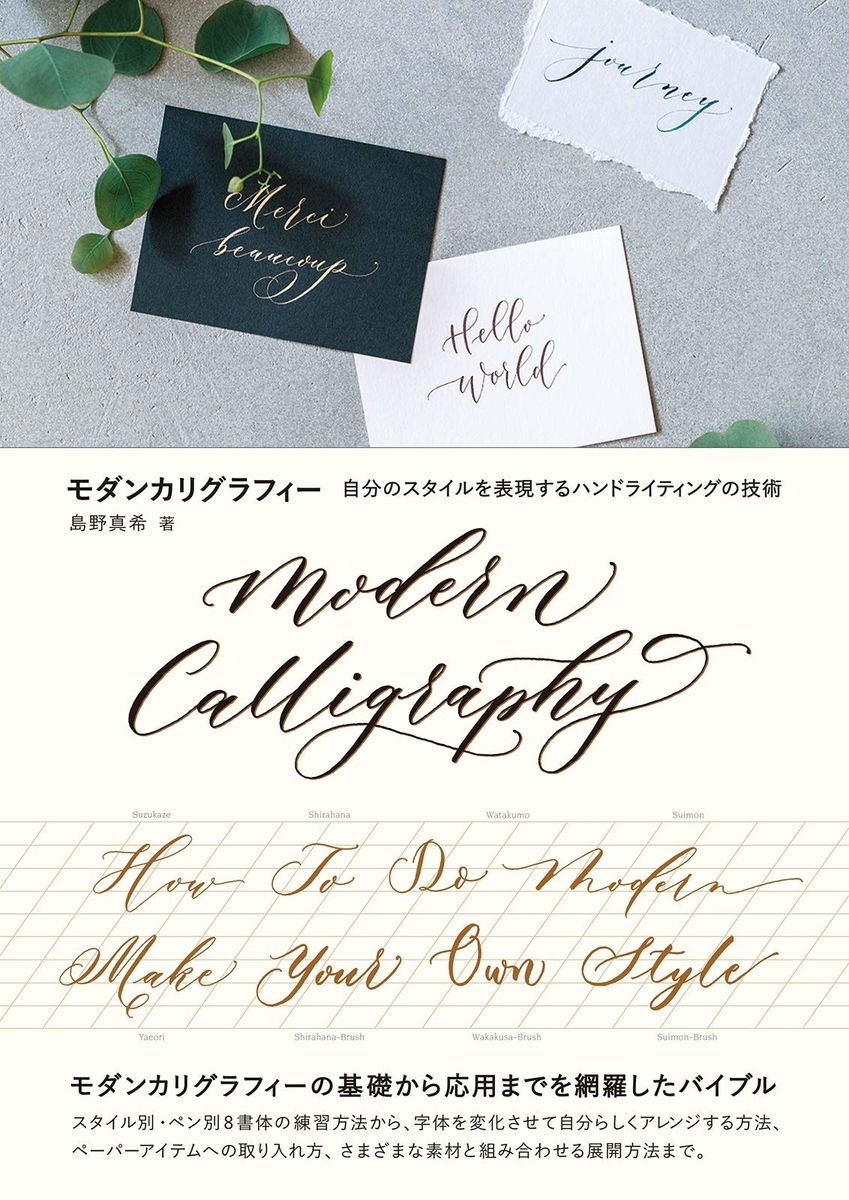
モダンカリグラフィー 自分のスタイルを表現するハンドライティングの技術/モダンカリグラフィー スタートセット
書道家、カリグラファーとして活躍する島野真希氏による日本初のモダンカリグラフィー指南書「モダンカリグラフィー 自分のスタイルを表現するハンドライティングの技術」がビー・エヌ・エヌ新社から2019年6月14日に発売された。
「モダンカリグラフィー 自分のスタイルを表現するハンドライティングの技術」は、実践的な練習方法でスタイル別・ペン別の8書体と例文をしっかり書けるようになる基礎編、自分らしい字体に変化させレイアウトや配色のデザインを考えるアレンジ編、イラストレーションと組み合わせたり紙以外の素材に書いたりアイテムに落とし込んでスタイリングする展開編、の3部構成になっている。
モダンカリグラフィーの基礎から応用の入り口までを網羅したバイブルとして、カリグラフィー初心者の方、書き文字をワンランクアップさせて別の趣味やお仕事と組み合わせたい方、自分だけの文字を追求してオリジナルの世界観を作りたい人までを対象に、幅広いリクエストに応えている。
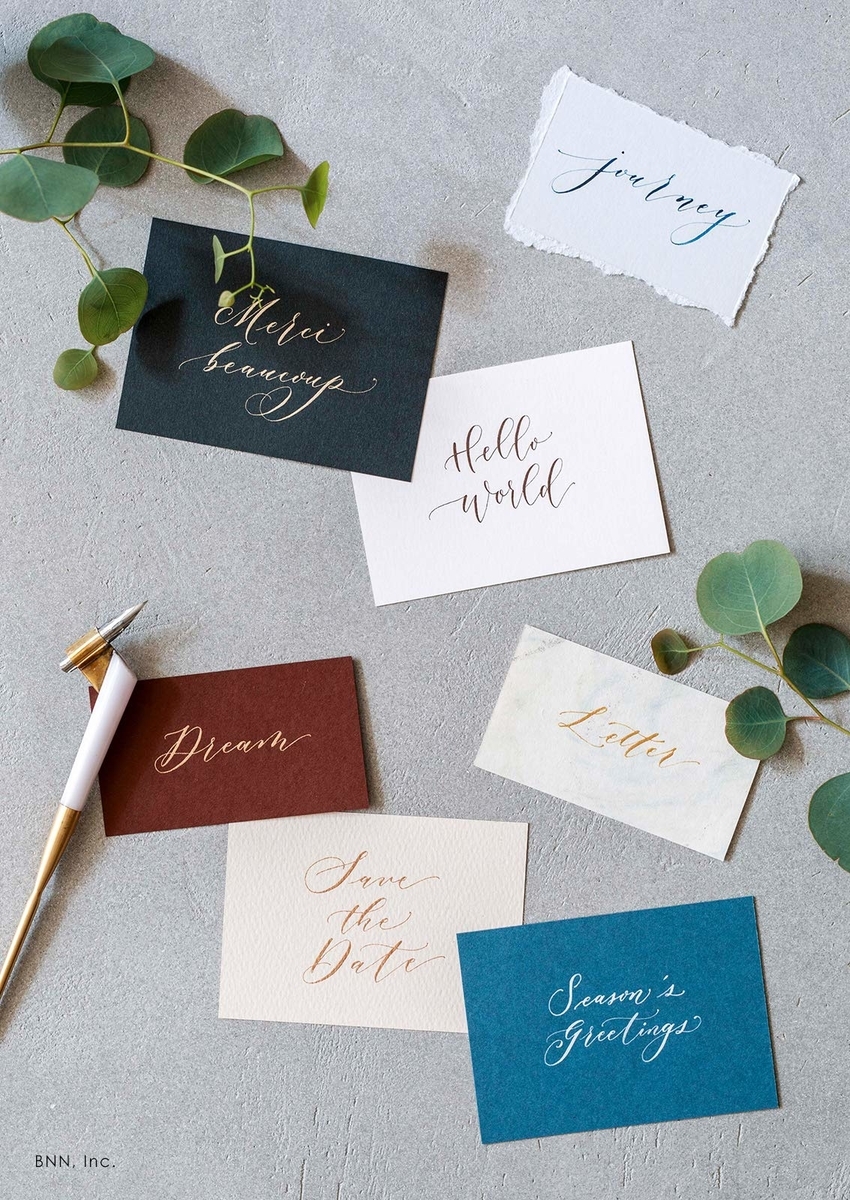
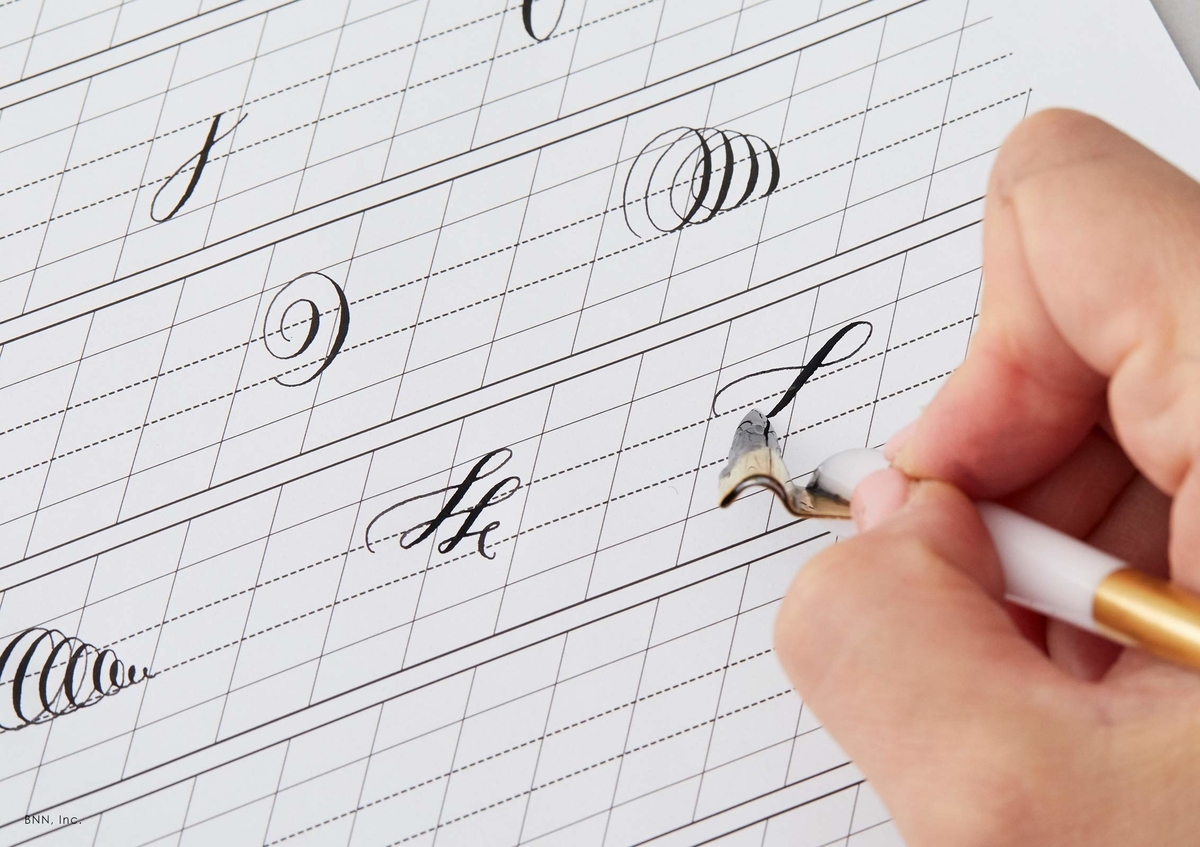
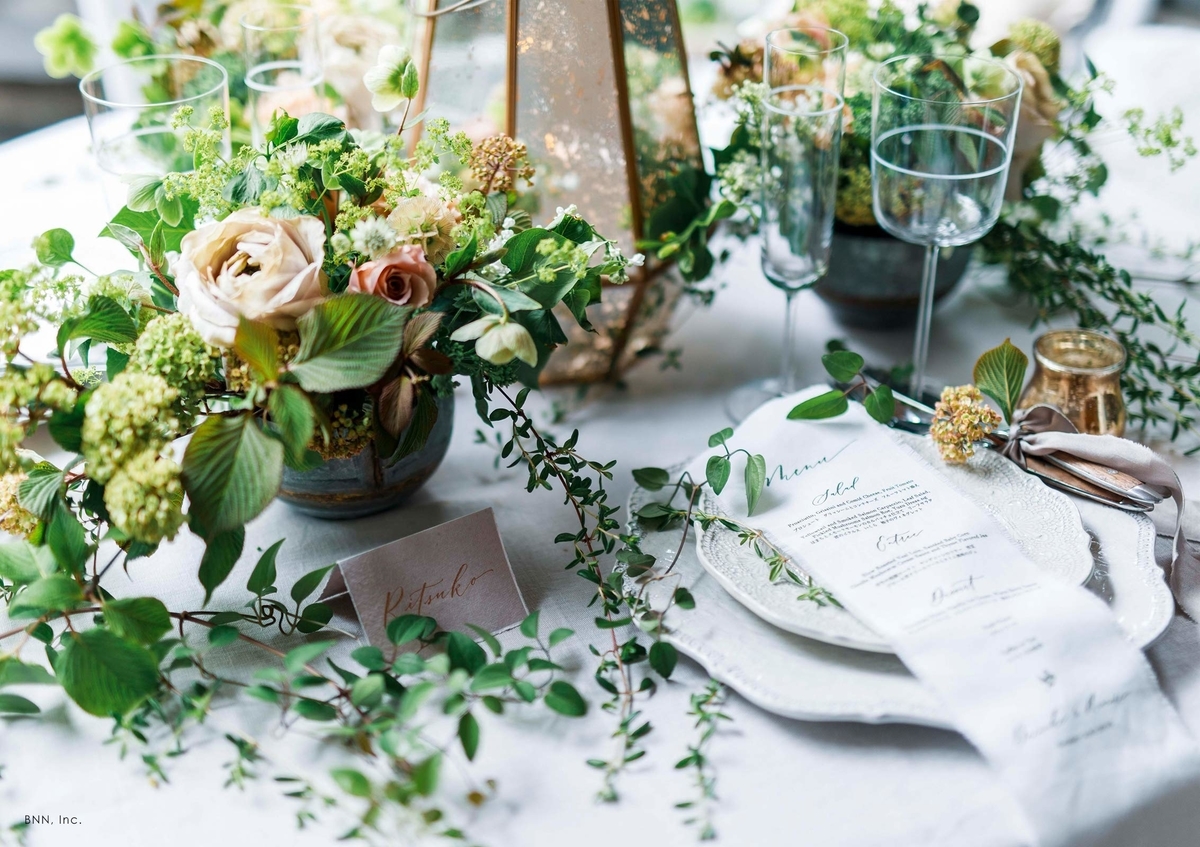
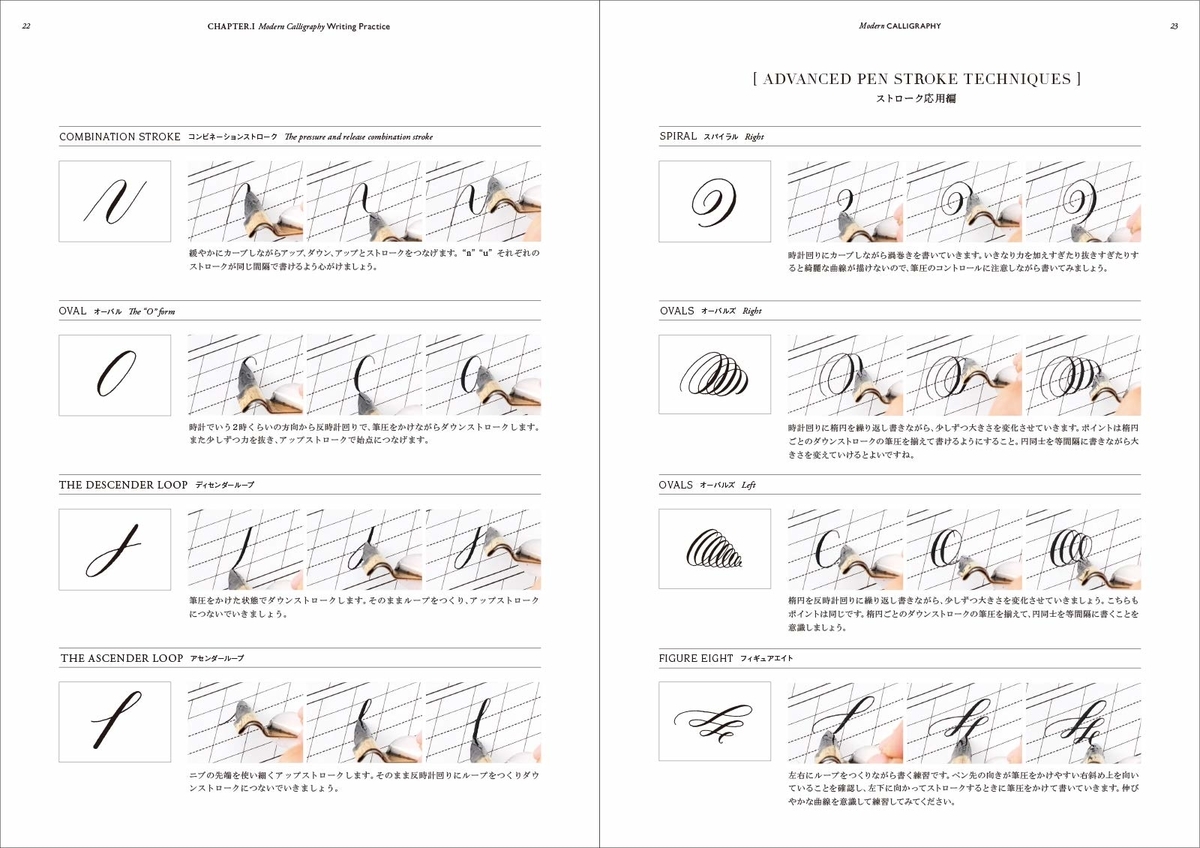
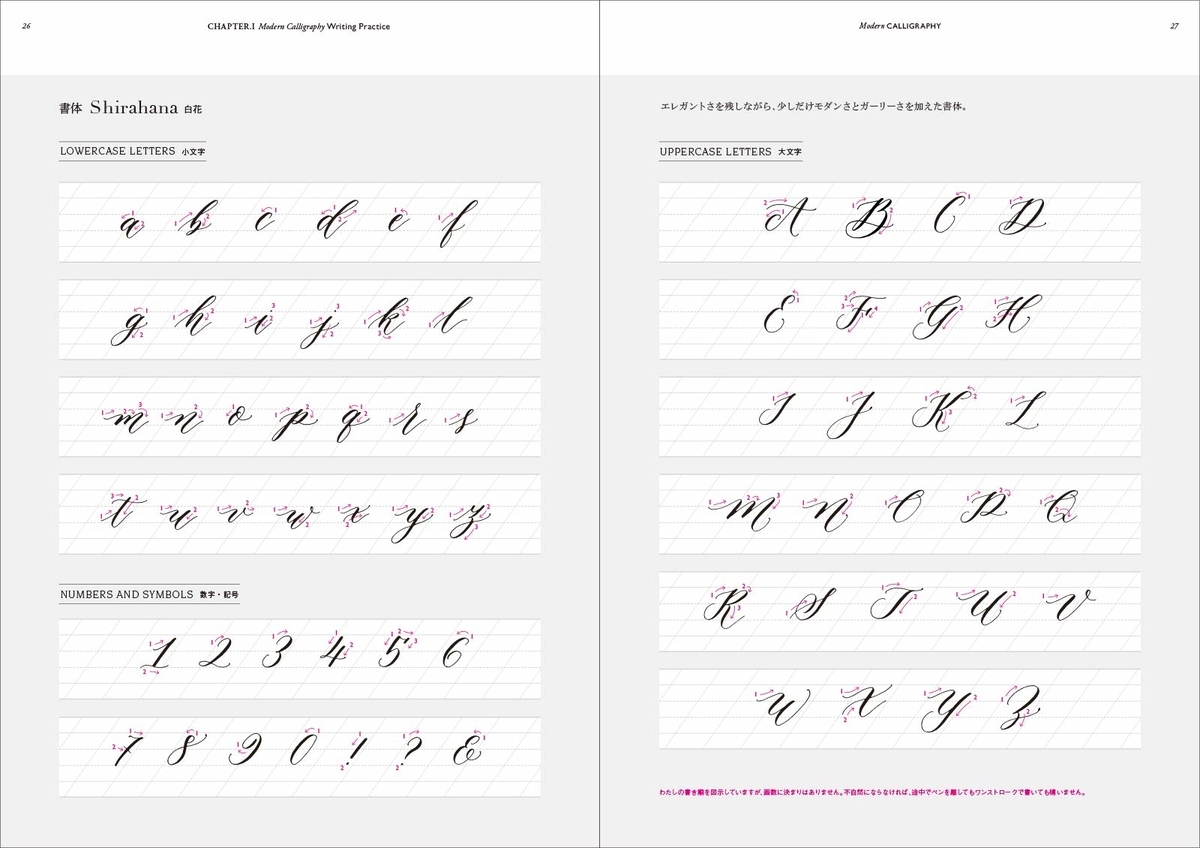
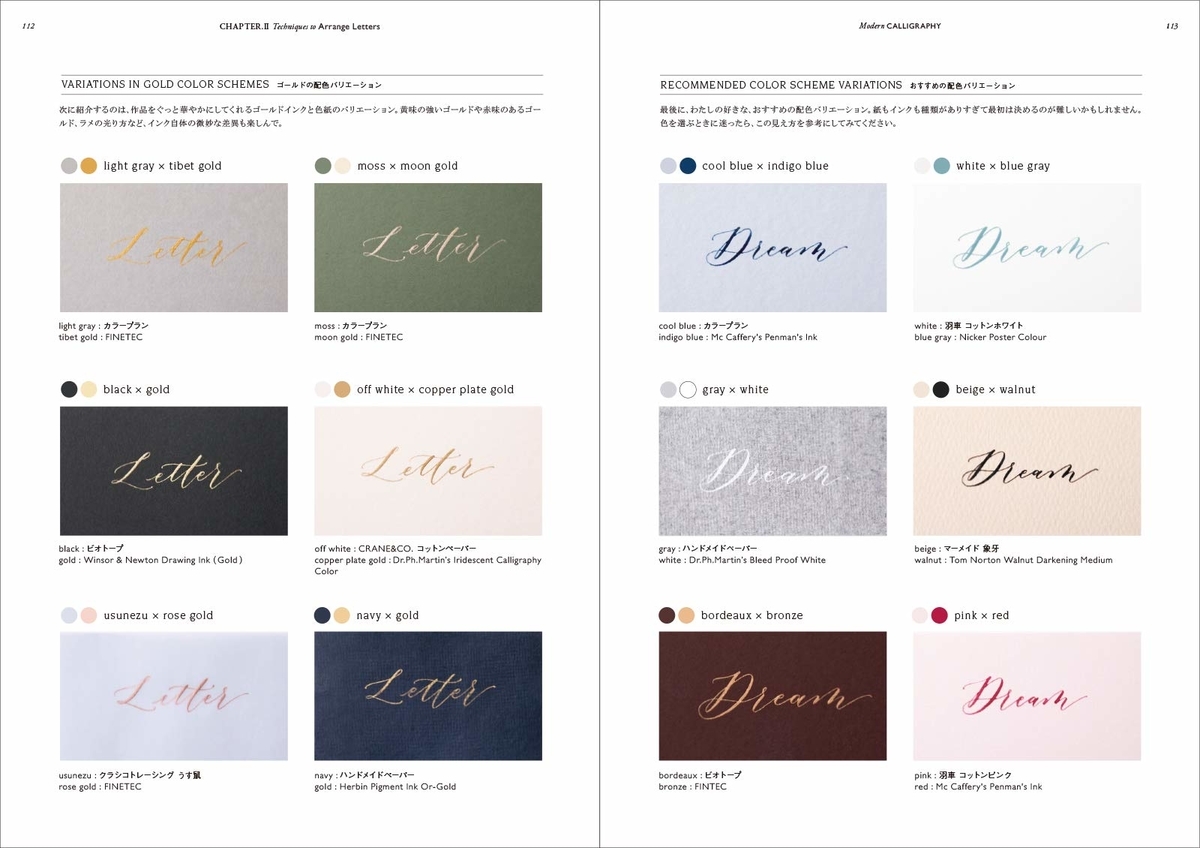
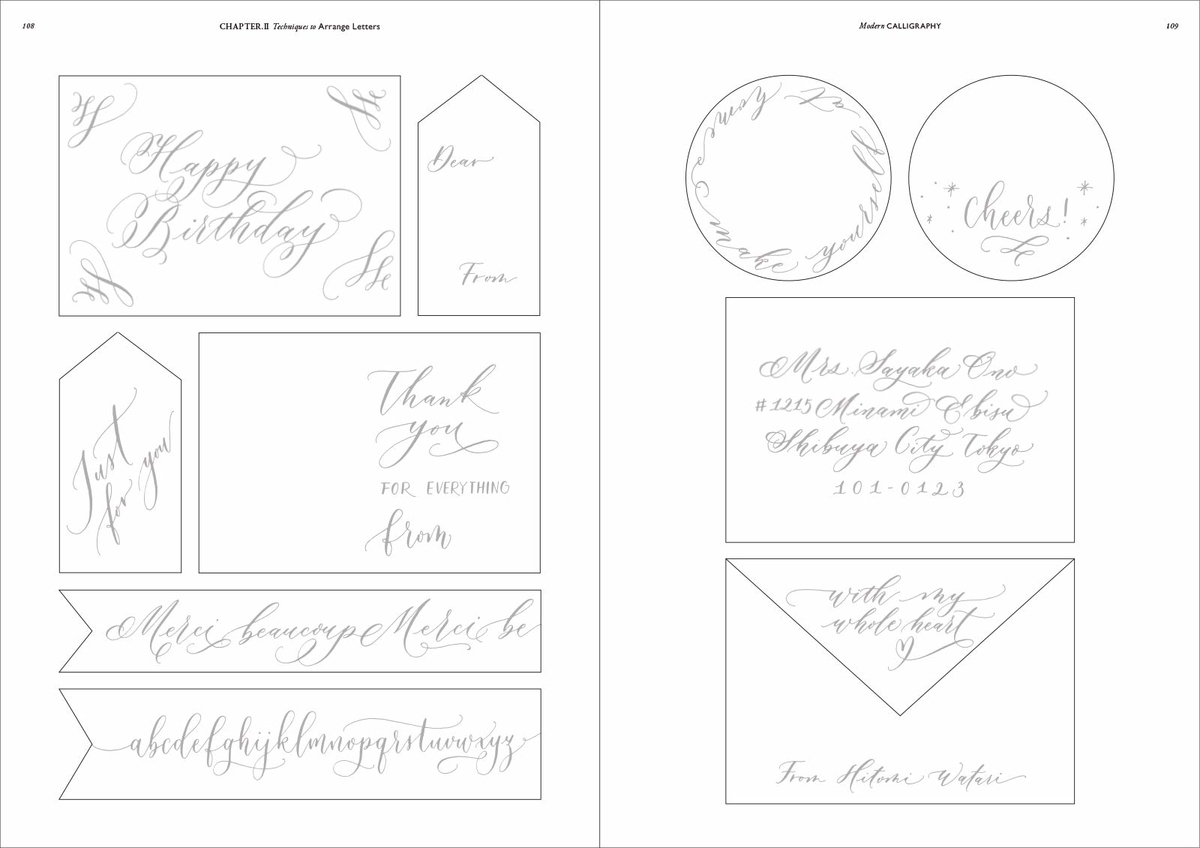
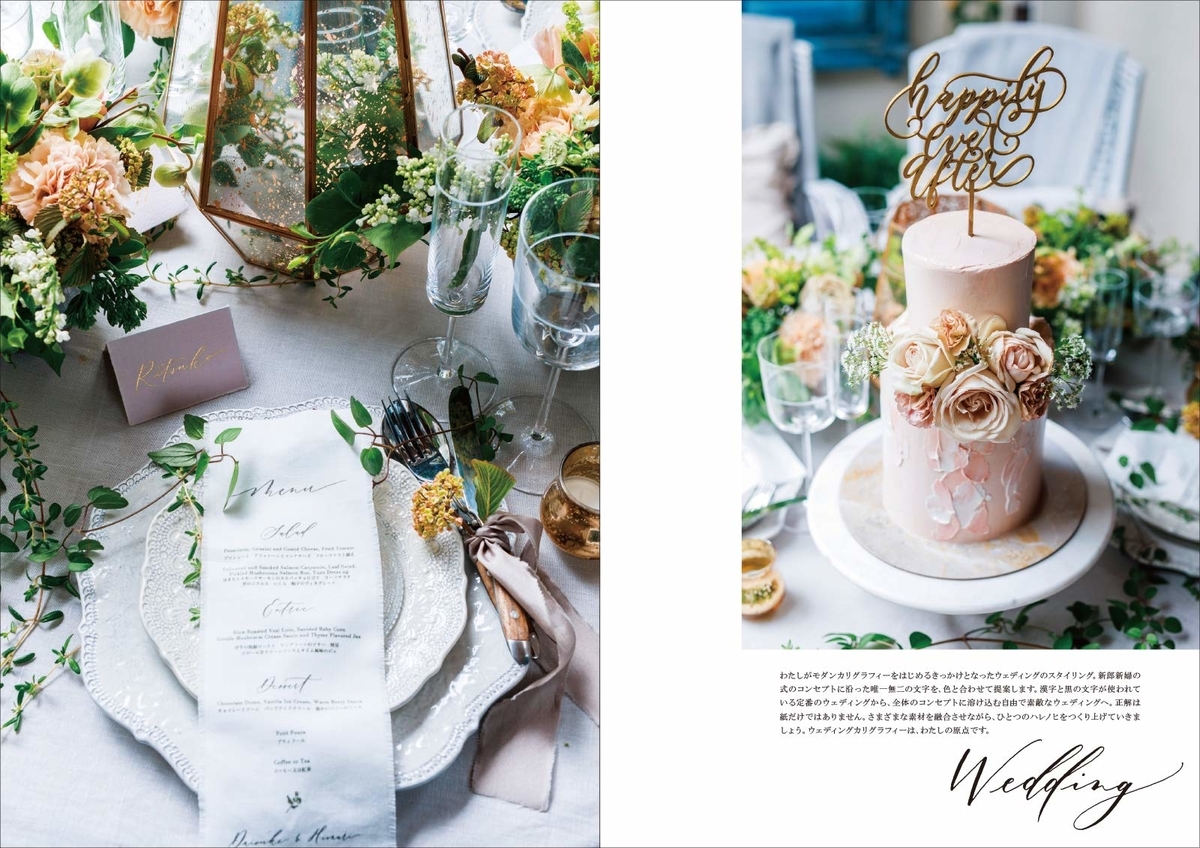
モダンカリグラフィー 自分のスタイルを表現するハンドライティングの技術
本書は、実践的な練習方法でスタイル別・ペン別の8書体と例文をしっかり書けるようになる手習い編、自分らしい字体に変化させレイアウトや配色のデザインを考えるアレンジ編、イラストレーションと組み合わせたり紙以外の素材に書いたりアイテムに落とし込んでスタイリングする展開編、の3部構成になっています。繊細なヘアラインが書けるポインテッドペンを中心に解説していますが、手軽に始められるブラッシュペンの書体も紹介しています。
モダンカリグラフィーの基礎から応用の入り口までを網羅したバイブルとして、素敵な文字が書きたいカリグラフィー初心者の方、書き文字をワンランクアップさせて別の趣味やお仕事と組み合わせたい方、イメージやシチュエーションに合わせた文字を生み出してオリジナルの世界観を作りたい方まで、幅広いリクエストに応えます。
※巻末には切り離して使えるお手本&ガイドシートが付属しています。
CHAPTER.I モダンカリグラフィーの手習い
モダンカリグラフィーの種類
はじめに使う道具
●ポインテッドペンで書くモダンカリグラフィー
1. ペンの扱い方
2. ストロークの練習
◇練習方法のススメ
基本のストローク
ストローク応用編
◇トラディショナルカリグラフィーとモダンカリグラフィー
書体 Shirahana 白花
書体 Suimon 水紋
書体 Watakumo 綿雲
書体 Suzukaze 涼風
書体 Yaeori 八重織
3. 文字のつなげ方
◇文字をモダンに見せるテクニック
●ブラッシュペンで書くモダンカリグラフィー
1. ペンの使い方
2. ストロークの練習
書体 Shirahana 白花
書体 Suimon 水紋
書体 Wakakusa 若草
例文
◇フレーズをモダンにみせるテクニック
フローリッシュアレンジ
◇下書きについて
1. フローリッシュのバリエーション
2. フローリッシュの書き方
3. フローリッシュの例文
CHAPTER.II 文字をアレンジするテクニック
さまざまな素材
オリジナルスタイルの探求
1. 人によって異なるモダンスタイルの特徴
2. 基本の書体から字体を変化させる
◇自分のスタイルを探す
書体のアレンジバリエーション
1. アレンジのポイント
2. 多彩なアレンジバリエーション
フレームに合わせたデザインバリエーション
配色のアレンジバリエーション
カードのデザイン
CHAPTER.III モダンカリグラフィーの展開
イラストとモダンカリグラフィー
さまざまな素材に書く
スタイリング
WEDDING
WRAPPING
BABY SHOWER
PARTY
スタイリングのコツ
自分の字でつくるオリジナルグッズ
絶対的な技術と人気を誇るカリグラファー・島野真希による日本初のモダンカリグラフィー指南書。文字を美しく見せるための手法「カリグラフィー」から派生した「モダンカリグラフィー」は、文字に自分らしさを表現できる自由度の高い現代的なハンドライティングの技術です。
本書は、実践的な練習方法でスタイル別・ペン別の8書体と例文をしっかり書けるようになる手習い編、自分らしい字体に変化させレイアウトや配色のデザインを考えるアレンジ編、イラストレーションと組み合わせたり紙以外の素材に書いたりアイテムに落とし込んでスタイリングする展開編、の3部構成になっています。繊細なヘアラインが書けるポインテッドペンを中心に解説していますが、手軽に始められるブラッシュペンの書体も紹介しています。
モダンカリグラフィーの基礎から応用の入り口までを網羅したバイブルとして、素敵な文字が書きたいカリグラフィー初心者の方、書き文字をワンランクアップさせて別の趣味やお仕事と組み合わせたい方、イメージやシチュエーションに合わせた文字を生み出してオリジナルの世界観を作りたい方まで、幅広いリクエストに応えます。
※巻末には切り離して使えるお手本&ガイドシートが付属しています。